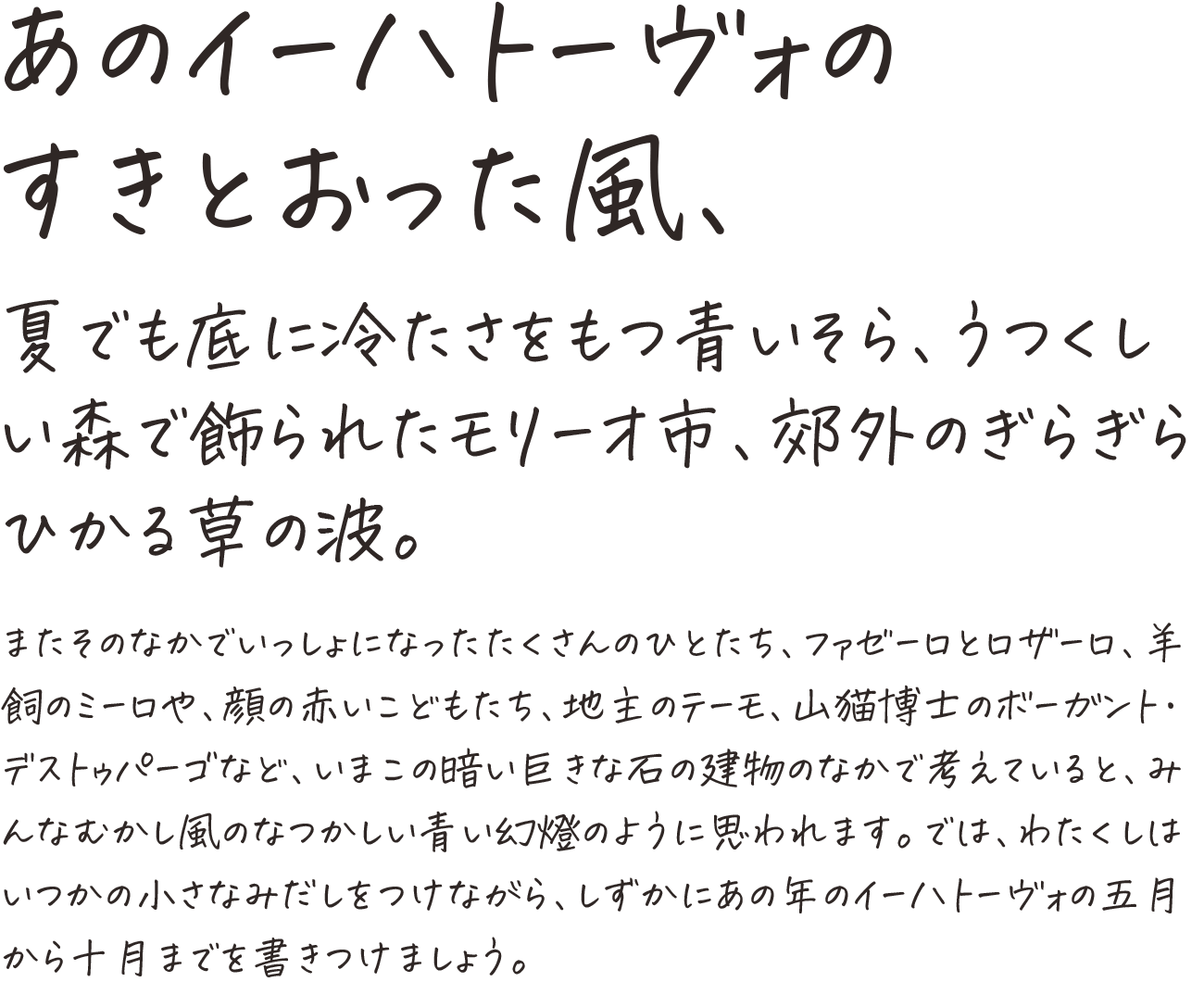
花とちょうちょ
手書きフォントの中でもとくに人気が高い、やや右上がりで動き・リズムを感じるかわいいフォント。デザインにはもちろん、写真やイラストへの文字入れにもおすすめ!矢印・下線など装飾用の素材も同梱されています。
太めで丸っこい「波とかもめ」や、万年筆で走り書きしたような「空とひこうき」も要チェック!
花とちょうちょの組見本